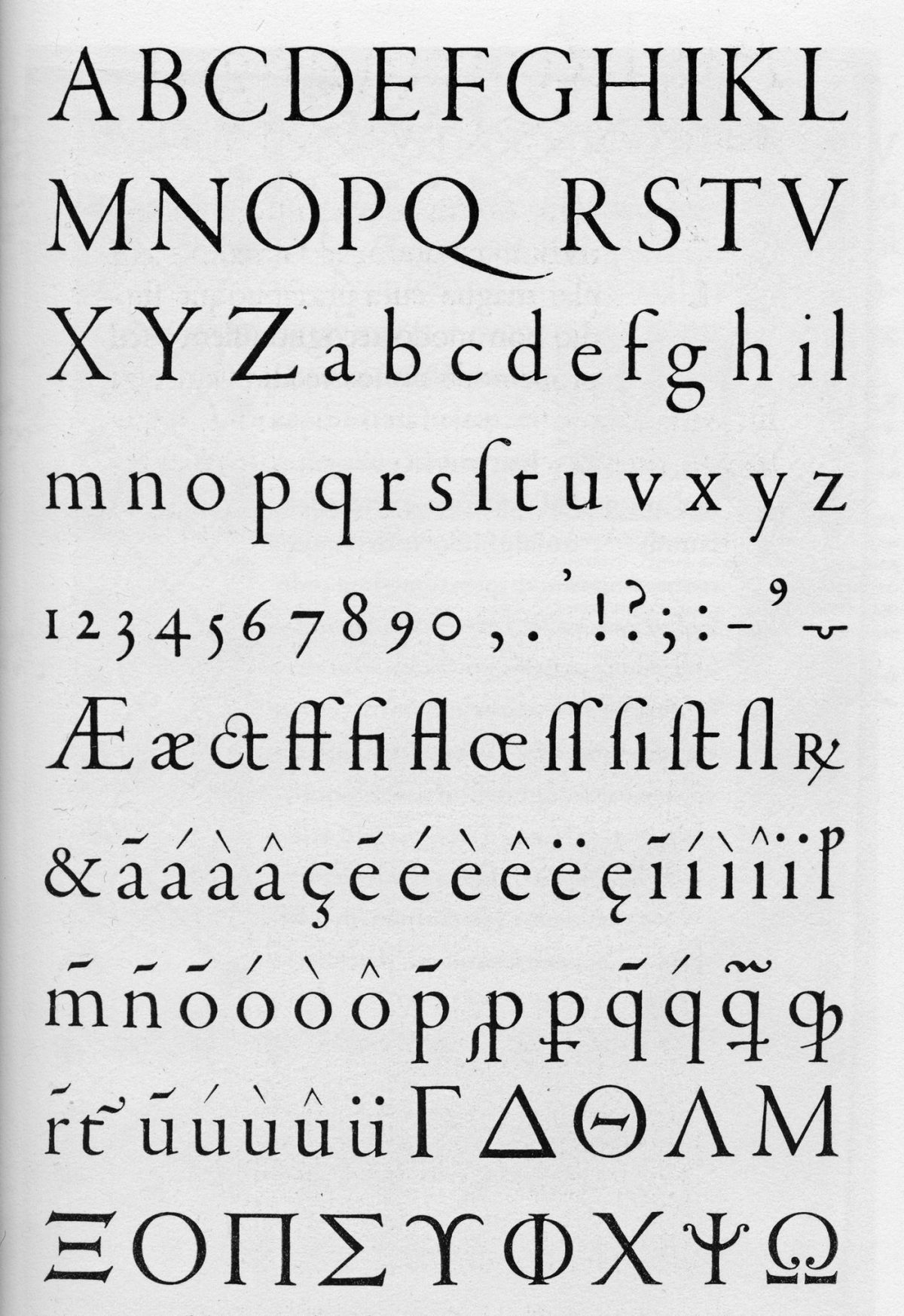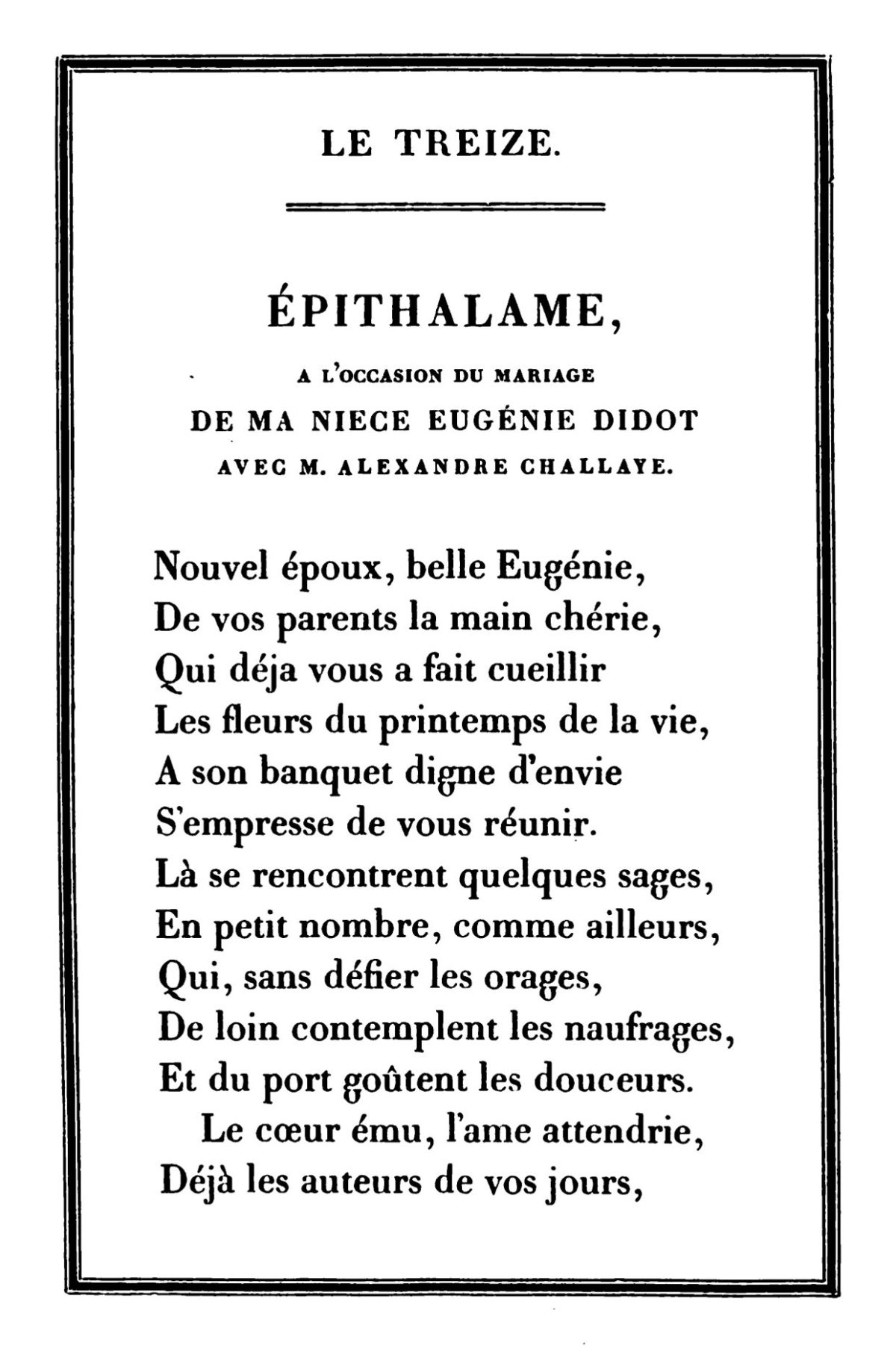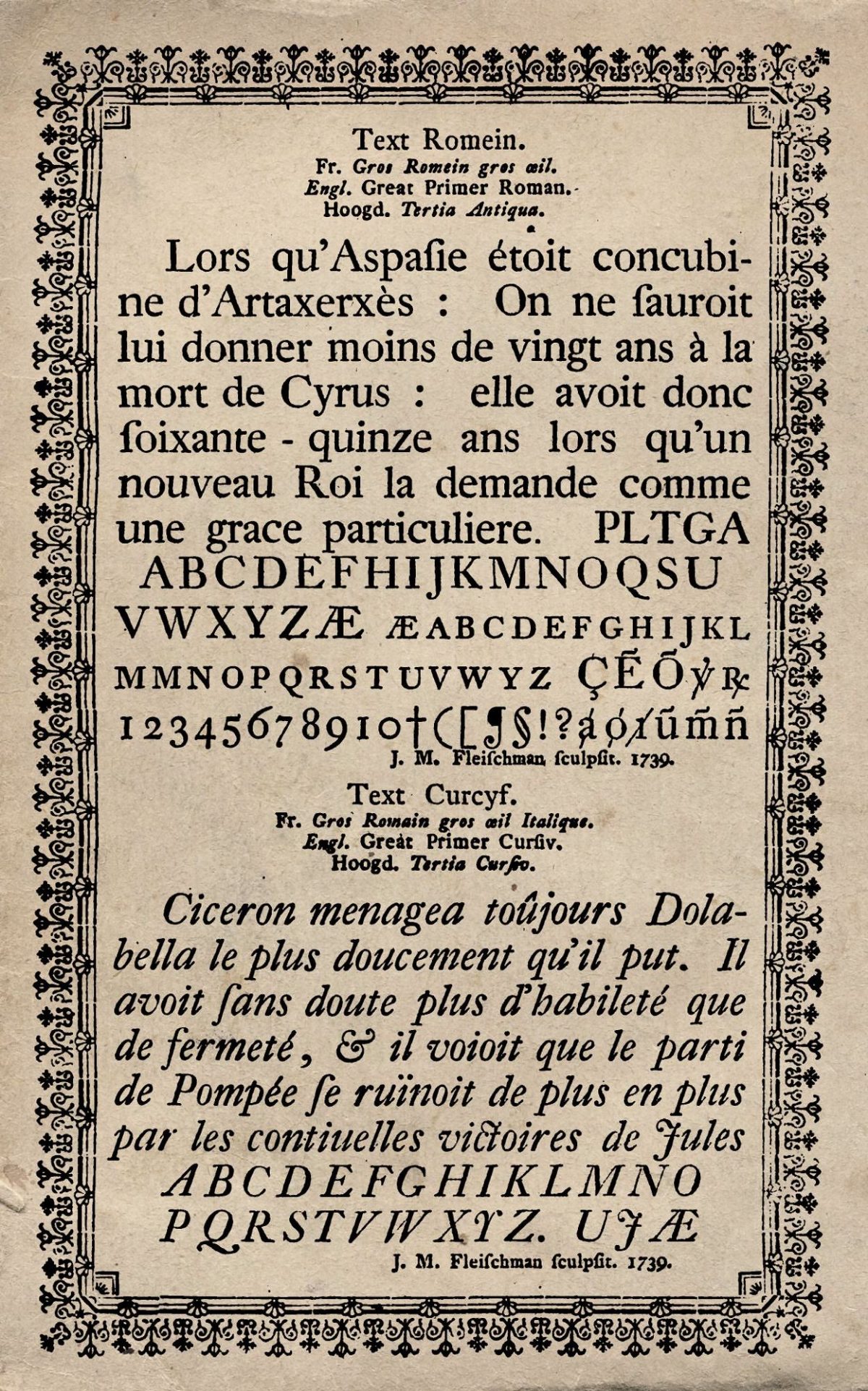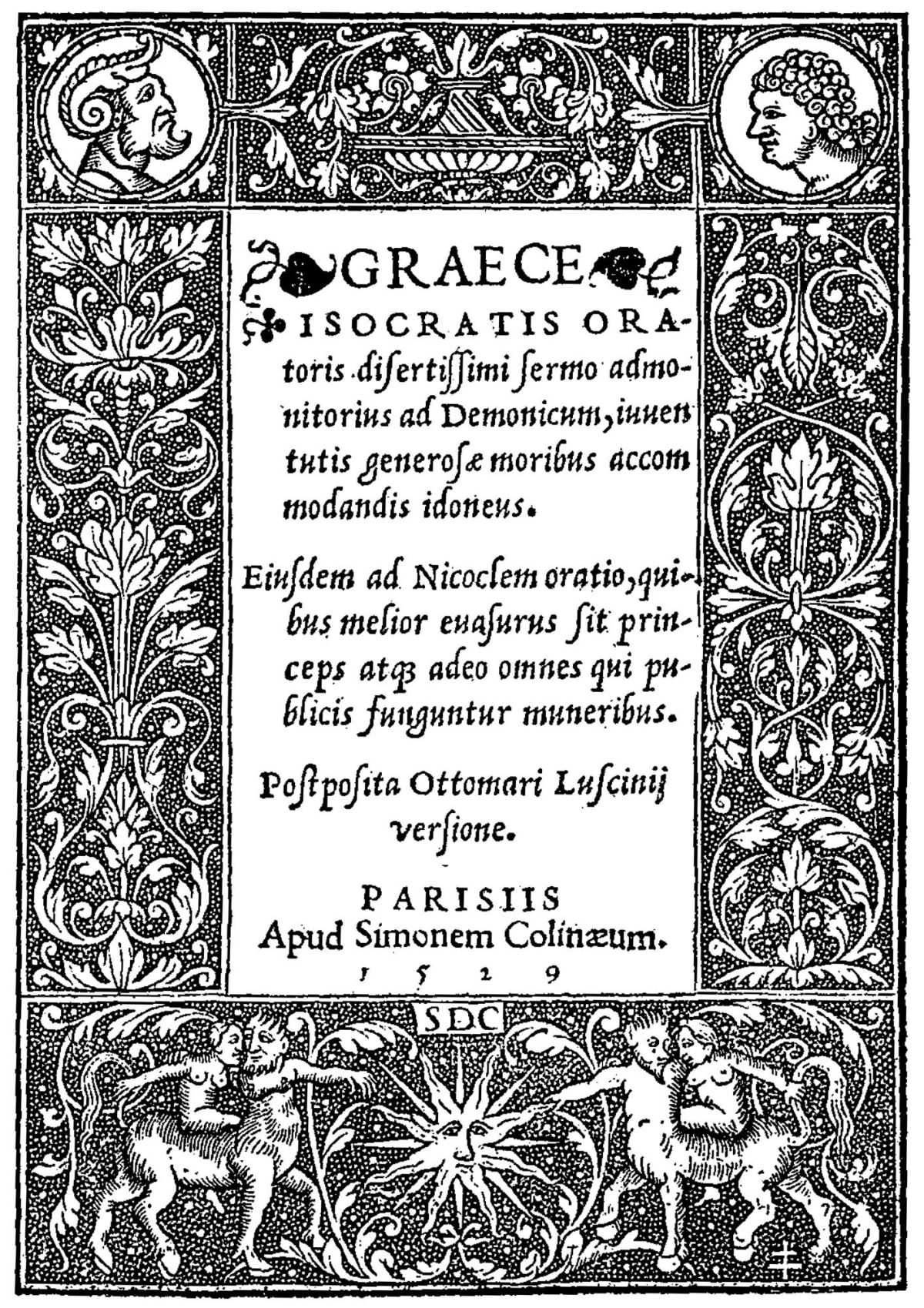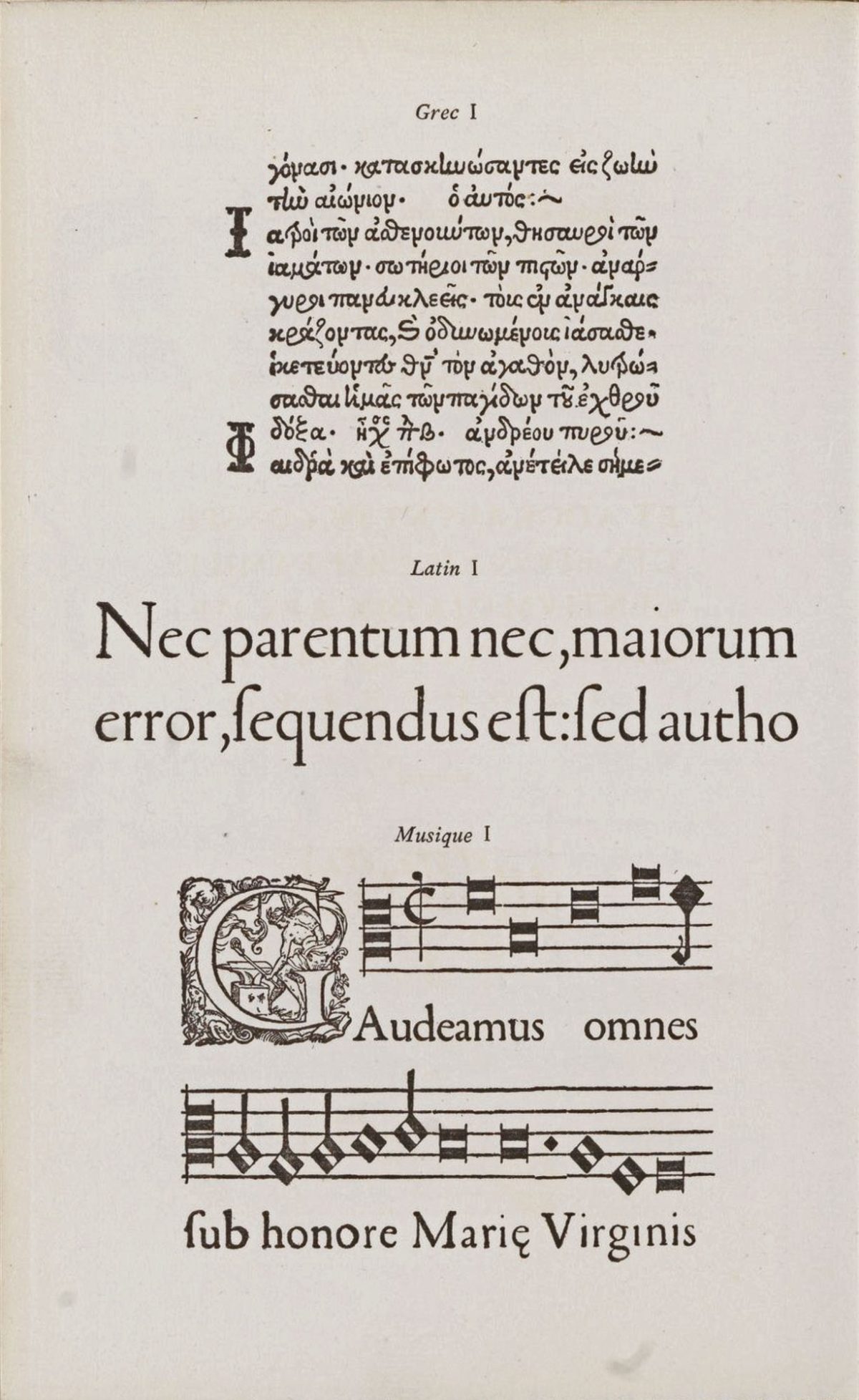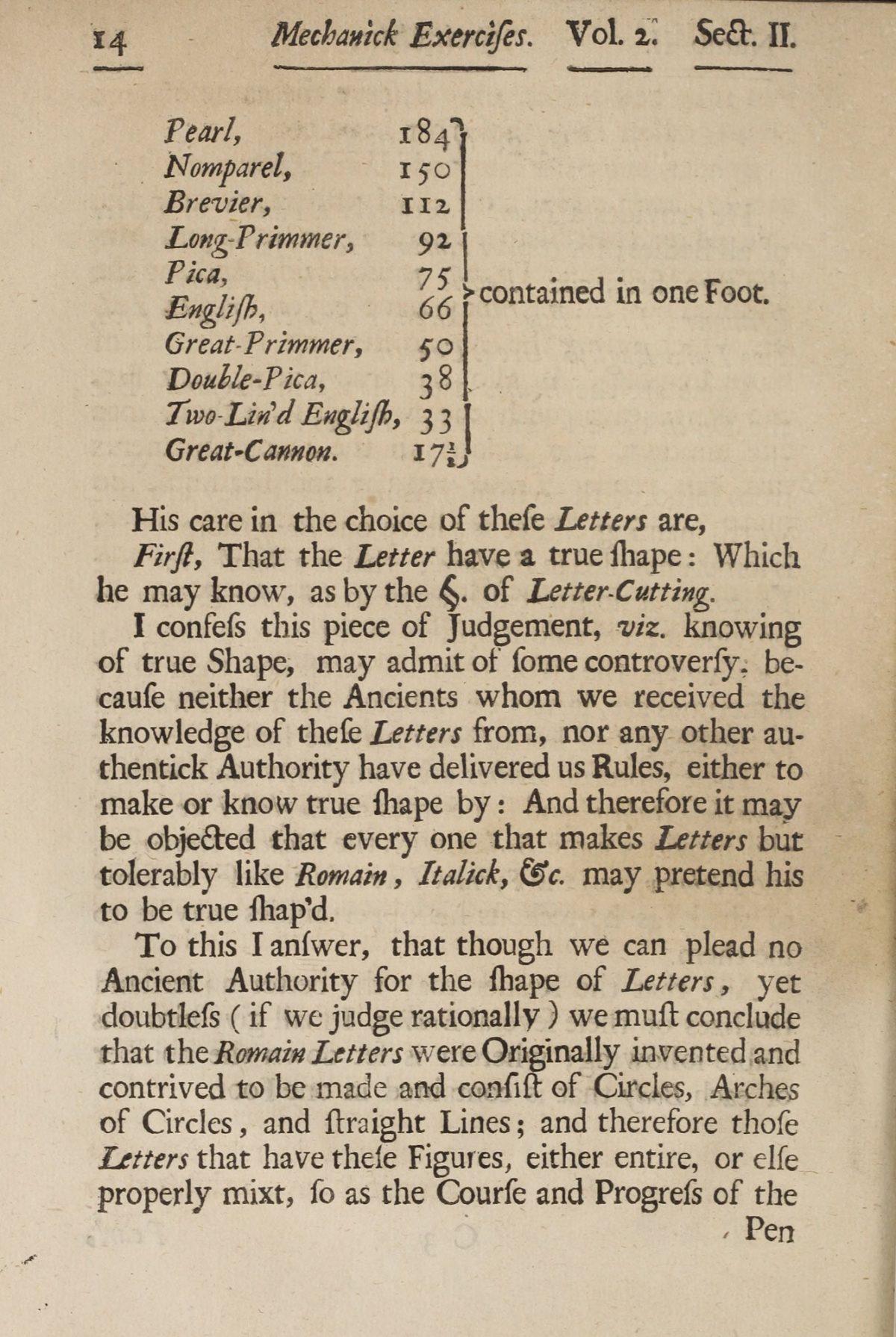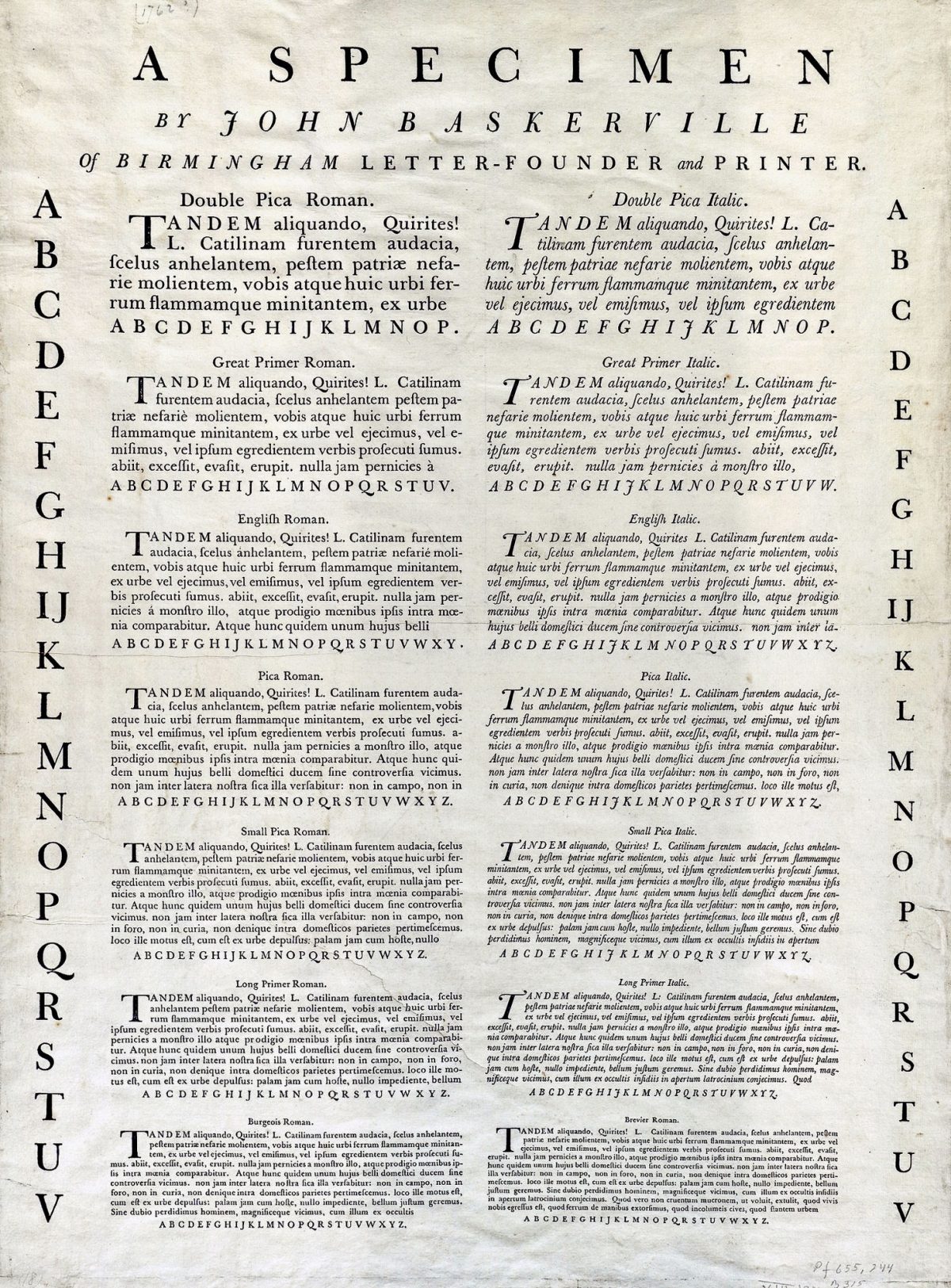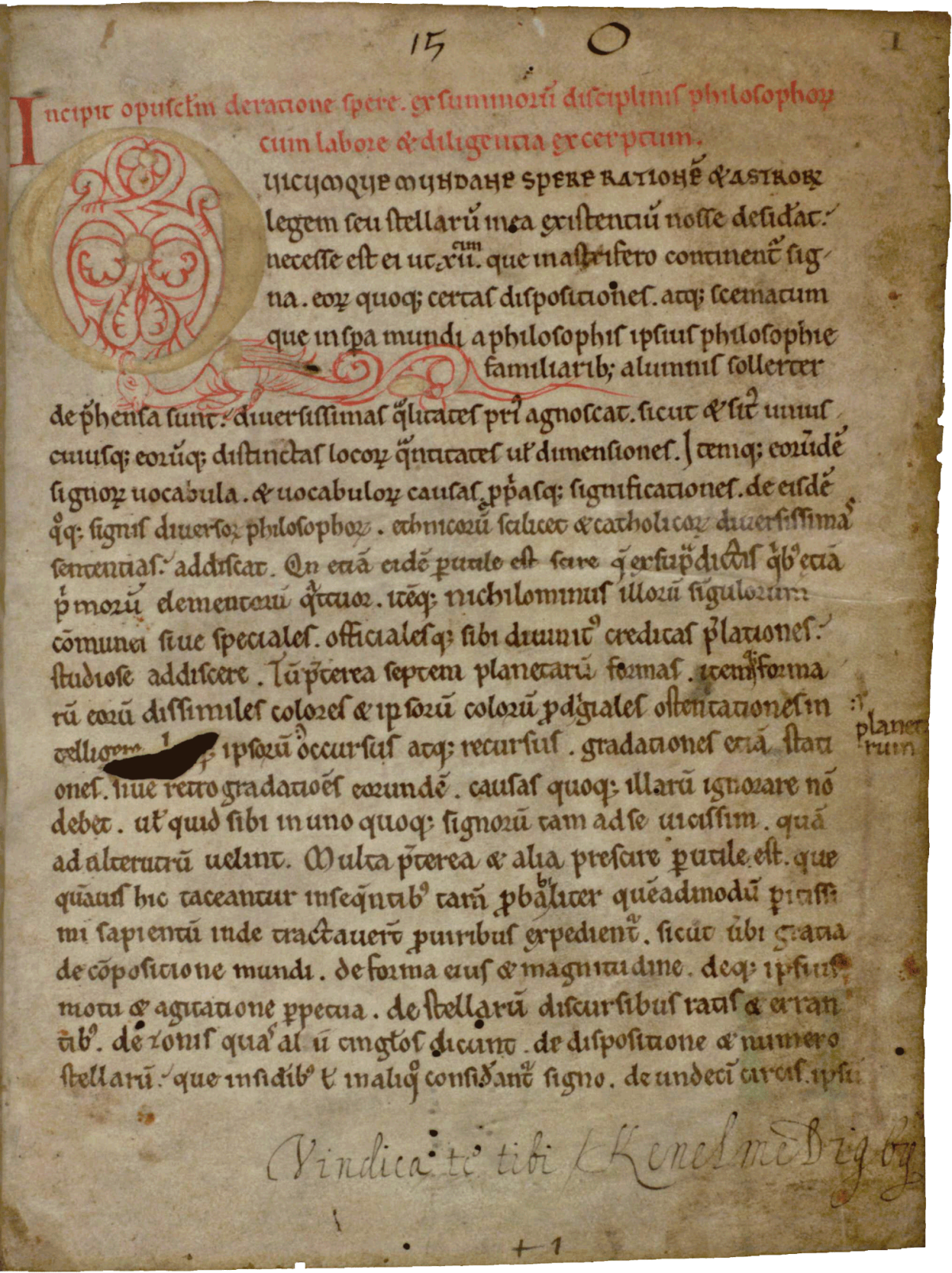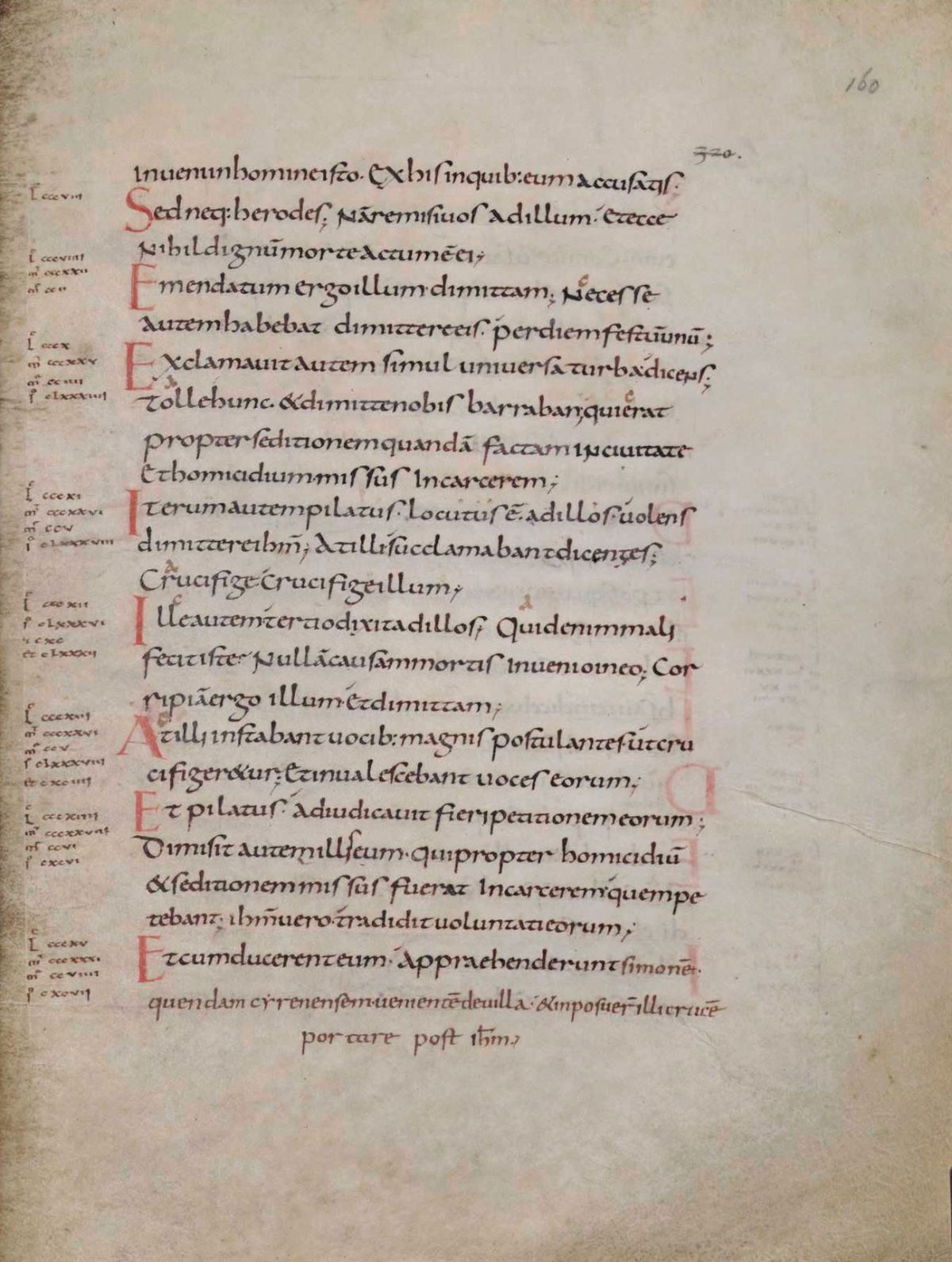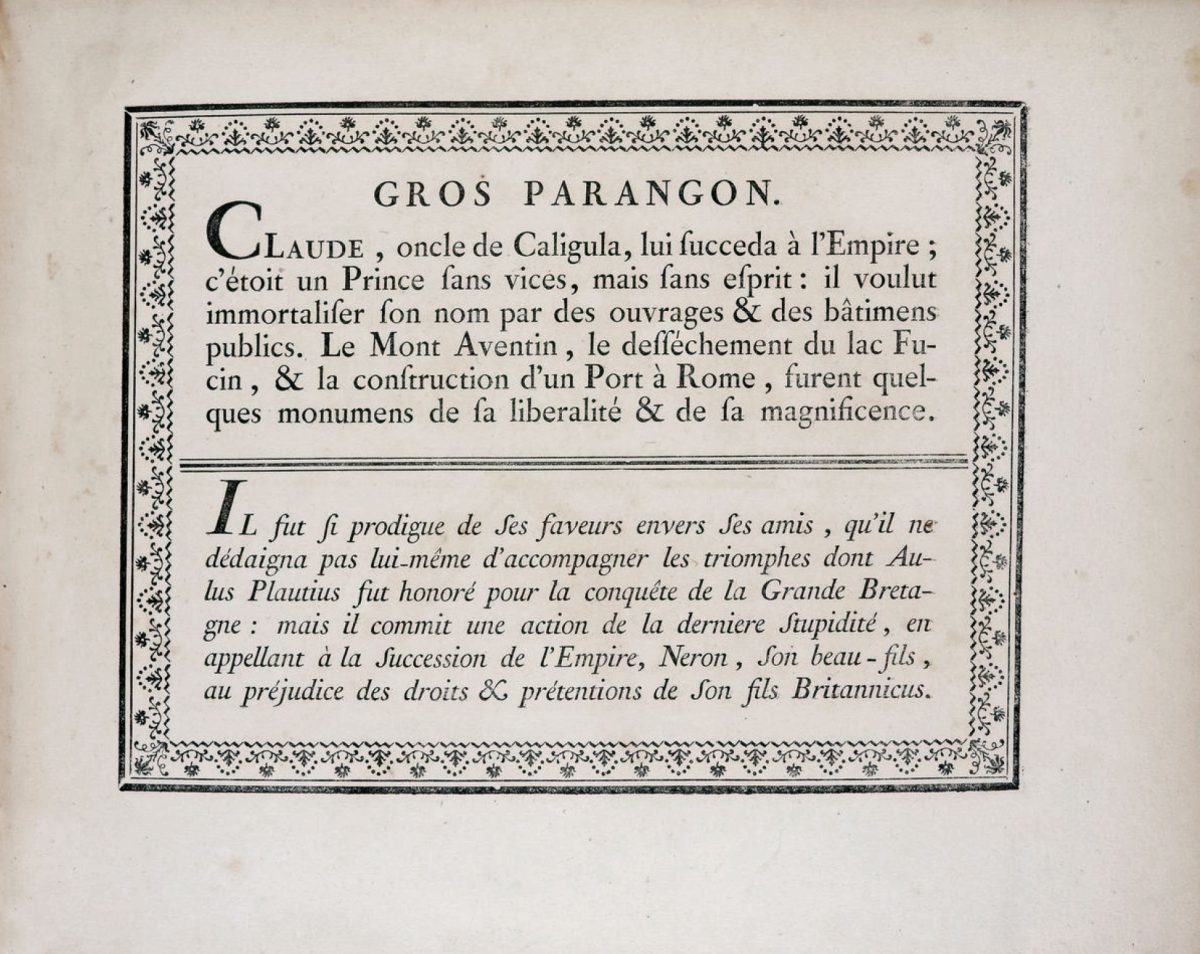
El espécimen tipográfico. ¿Herramienta de trabajo u objeto de placer? [Parte I]
El universo de la tipografía está lleno de sutilezas y detalles, de formas que transmiten ideologías a través de sus trazos. El espécimen tipográfico es el mundo que antecede a la puesta en página y donde sobran pretextos para observar el color de la trama, el contraste, el espacio entre las líneas y las letras; es el lugar donde se originan las combinaciones infinitas de los signos que esperan inertes y que aún no toman sentido en un discurso, pero que son para disfrutarse. Esta reflexión pretende esbozar el vasto mundo de una herramienta tan importante, poco recurrida y bastante desaprovechada en nuestros días. Para entenderla, es preciso conocer sus orígenes y el desarrollo que tuvo en las distintas épocas. (Esta es la primera de tres entregas del texto.)
Qué es un espécimen tipográfico
Según la rae 1, la palabra espécimen refiere a una «muestra, modelo, ejemplar, normalmente con las características de su especie muy bien definidas», pero, si nos referimos al espécimen tipográfico podemos imaginarnos una impresión de factura perfecta y donde la letra luce por sí sola, sin defectos, bien definida y mostrando todas sus cualidades formales. De ahí que el espécimen tipográfico tenga formas tan diversas que van desde una simple hoja hasta publicaciones bellísimas completamente ornamentadas y de estampa impecable, finamente encuadernadas y que no escatiman en número de páginas o detalles. En la actualidad, este ejemplar puede tomar la forma de una edición digital o animación compleja que hace alarde de las posibilidades de la programación y del color luz. Aún así, este objeto se considera más como catálogo de fuentes tipográficas que un manual técnico de uso o, incluso, una publicación artística, aunque la finalidad ha sido siempre la de exaltar las características y la belleza de las letras que buscan atrapar la mirada de los lectores o de los transeúntes que deambulan frente a los carteles de los escaparates y, por qué no, a aquéllos que ahora navegan en tabletas digitales o teléfonos móviles en la infinita red.
Imagen 1. Espécimen de la Gros Canon de Garamond [ca. 1530]. Tipos impresos y fundidos a partir de las matrices en el Museo Plantin-Moretus. Tomado de A View of Early Typography Up to About 1600 de Harry Carter, fig. 69.
Sin embargo, este objeto no hubiese adquirido el valor que hoy tiene de no haber sido por los coleccionistas y los bibliotecarios que tuvieron interés en recopilar estas muestras tipográficas, muchas de ellas impresas por las manos de los mismo diseñadores y cortadores de punzones como Claude Garamond (imagen 1), Pierre Simon Fournier, John Baskerville o Giambattista Bodoni, aunque, también, producidas por las grandes fundidoras como Stempel, American Type Founders o Berthold, que procuraron una buena impresión de los tipos de letra.
Cada quien ideó sus propias muestras en función de sus necesidades, estándares y, sobre todo, del espíritu de la época, muchas veces adecuadas a la moda imperante; sin embargo, es evidente que tanto el espécimen como los catálogos de tipos ha servido de modelos e inspiración para los nuevos diseños de letra que van desde reinterpretaciones y rescates históricos, investigaciones de todo tipo, hasta creaciones originales.
Por último, me parece importante acotar que en este escrito me referiré indistintamente al espécimen y al catálogo para hablar de muestras, y debo aclarar que no se trata de lo mismo y que cada uno obedece a necesidades distintas, como se precisará más adelante en el apartado «Tipos de espécimen».
Imagen 2 [izquierda]. Capital Cuadrata [siglo IV]. colección Veterum Fragmentorum Manuscriptis Codicibus detractorum, t. I, p. 12. San Galo: Biblioteca de la Abadía de San Galo. Disponible en: https://goo.gl/bPQPZn.
Imagen 3 [derecha]. Capital Rústica Romana [ca. 830]. Cod. 165. Pergamino, 219 ff., 32.5 x 24.5 cm. Tours: Abadía de San Martín, Berna, Burgerbibliothek. https://goo.gl/GPqZ35
Los orígenes de la tipografía: la sistematización de la escritura
La tipografía no se inventó de la noche a la mañana, años de evolución de la escritura tuvieron injerencia directa en este hecho, no obstante, la sistematización de la escritura tuvo su origen en el trabajo de los calígrafos griegos y romanos quienes, a través de los modelos de escritura como la Uncial (s. III d. C.), Capital Monumental (s. III a. C.), la Capital Quadrata (s. I a. C., imagen 2) o la Capital Rústica (s. I d.C., imagen 3), establecieron el ductus 2 de trazo de los signos con la finalidad de mantener la unidad en los modelos. Tal fue el alcance del poder de la escritura que, hacia el 800 d.C., el emperador Carlomagno, apoyado por la iglesia, reunió un grupo de teólogos y eruditos que concibieron tanto los textos sagrados y litúrgicos como las reformas escolares que el imperio romano difundió en sus territorios y en los que se empleó un modelo de letra clave para la evolución de la escritura: la minúscula carolina, orquestada por Alcuino de York, y que constituye la base de nuestro alfabeto actual de caja baja.
Imagen 4. Minúscula Carolina. Biblia Vulgata, f. 160v. Londres: British Library, MS Add. 11848. https://goo.gl/kohHF3
Mediavilla (2009: 140-142) comenta que hacia el siglo IX surgieron numerosos talleres de copistas que dieron origen a los scriptoria 3 y de éstos destacó el de Saint Martin de Tours, en Francia, por la calidad de su producción que estuvo bajo la dirección del abad Alcuino. Aquí se perfeccionó el modelo carolino (imagen 4), cuya versión tardía (hacia el siglo XII y XIII) sirviera de inspiración para la letra humanista del Renacimiento italiano. Como era de esperarse, el modelo instaurado evolucionó y poco a poco fue adoptando rasgos insulares que fueron quebrando la forma de los signos. Esta transición que duró cerca de tres siglos y que se consolidó hasta finales del siglo XIII, dio origen a un nuevo modelo que también obedeció a «la aceleración del ritmo de escritura, la escasez de pergamino y la búsqueda de una nueva estética» (Mediavilla, 2009: 150) que ya era evidente en la propuesta arquitectónica.
Imagen 5. “Protogótica” [siglo XII]. Opusculum de ratione spere, f. 1r. Oxford: Bodleian Library, MS. Digby 83. https://surl.li/hyqqnp
Los modelos góticos primitivos datan del año 1070 hasta principios del siglo XIII (imagen 5), pero, no fue sino hasta mediados del XIII que se adoptó la escritura gótica de textura 4 cuyo ductus de trazo incorporó reglas específicas en lo referente al ritmo del espacio entre letras y la forma que debían tener las terminales de los signos. Los estilos de letra se diseminaron y diversificaron por toda Europa y en cada región adoptaron formas distintas.
No hay registro físico de algún tipo de guía para el trazo, pero, al igual que los modelos romanos, se aprecia el uso de reglas estrictas y muchas similitudes en las variantes, tanto en las proporciones, espacio entre letras, el ángulo de escritura, como en los rasgos y las terminales de los distintos estilos de letra góticos. La gótica de textura de finales del siglo XIV era tan precisa y estaba tan normada que las reglas de escritura sirvieron de base para consolidar uno de los inventos más grandes de la humanidad: la imprenta, justo a mediados del siglo XV (imagen 6).